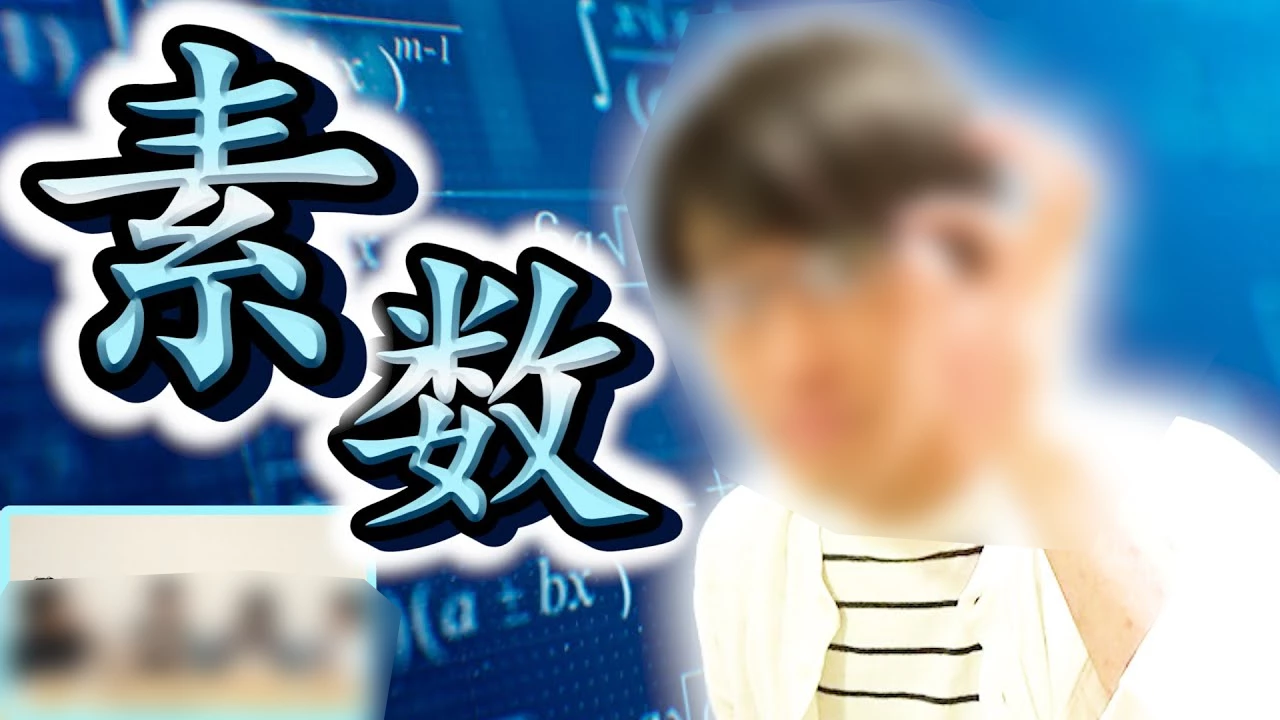
SSyu_EditParticipant6 years agoJul 9, 2020 2:55 AM UTCQuestionこのテキスト(フォント)の表現方法について1 reply170 viewsTranslate↓の「素数」という文字の表し方を知りたいです実は最近までGIMPを使っており、PSに乗り換えたばかりで初歩的なものも分からないですテキストを複製し右上などにずらしたりして立体感を出したりといったことはできるのですが、このフォントだと文字の中央部が盛り上がっているようになっていますご存知の方いましたら教えて頂けると幸いです周りの黒い影をずらしたような表現もどうすれば可能なのか知りたいですGIMPだと地道にレイヤーを複製して重ねるか、手作業で塗りつぶすしかなくて困っています macOSWindows